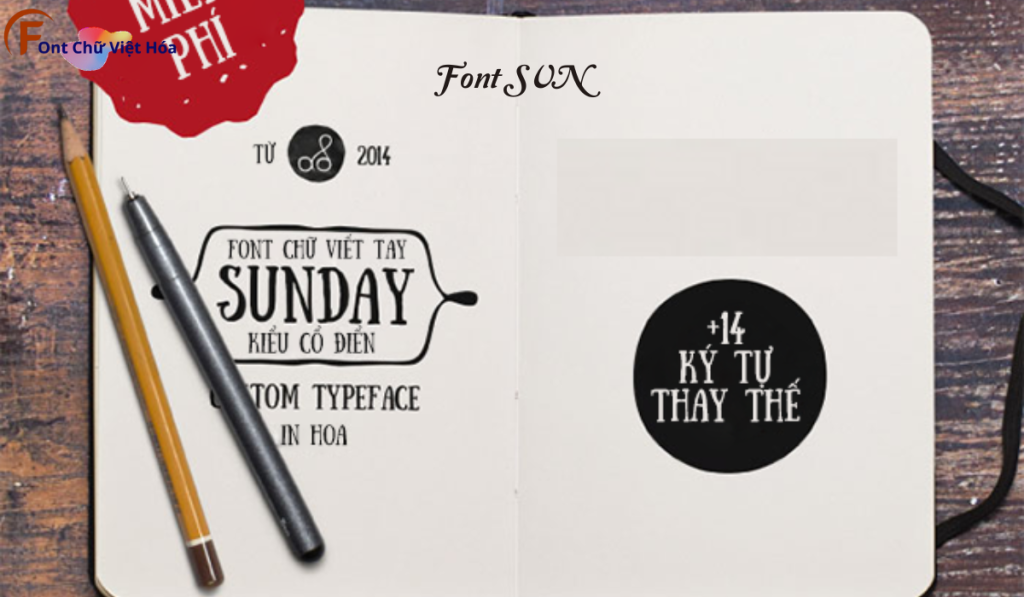
Font SVN Sunday Việt Hóa
Phân loại: Cá tính, Nét vẽ thủ công
Độ dày: Mỏng
Font SVN Sunday Việt Hóa là một font chữ không chân hiện đại, thuộc bộ font SVN. Được thiết kế với mục tiêu mang lại sự tinh tế và thanh lịch, font này phù hợp cho các dự án thiết kế như website, tài liệu, và bao bì sản phẩm. Với các nét chữ rõ ràng và độ dày đều đặn, Font SVN Sunday Việt Hóa không chỉ dễ đọc mà còn tạo cảm giác chuyên nghiệp. Việc Việt hóa font giúp người dùng dễ dàng sử dụng trong các thiết kế tiếng Việt, mang lại sự tiện lợi và thẩm mỹ cao.